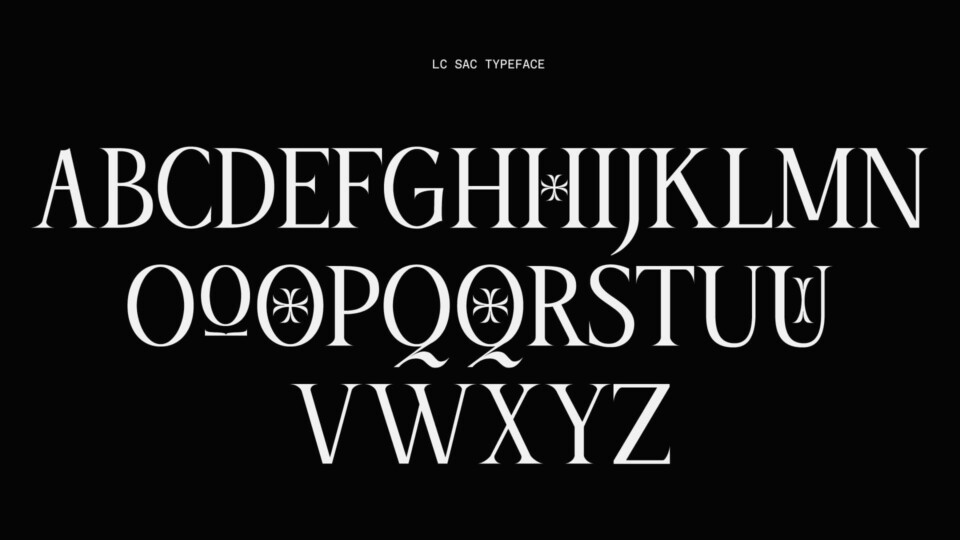
Font tiếng việt LC Sac Display – Nguyễn Quang Duy
Giới thiệu về Font tiếng việt LC Sac Display – Nguyễn Quang Duy
Trong thế giới sáng tạo, việc lựa chọn một bộ Font Miễn Phí chất lượng luôn là ưu tiên hàng đầu của các nhà thiết kế trẻ. Bộ Font tiếng việt LC Sac Display – Nguyễn Quang Duy là một tác phẩm typography đầy ấn tượng, mang phong cách hiện đại và cá tính. Đây là thành quả sáng tạo của tác giả Nguyễn Quang Duy, được tinh chỉnh kỹ lưỡng để phù hợp với bảng mã tiếng Việt, giúp người dùng không còn lo lắng về lỗi font khi soạn thảo nội dung hay làm các ấn phẩm truyền thông.
Đặc điểm nổi bật của bộ font chữ này
Sở hữu những đường nét thanh mảnh nhưng vô cùng dứt khoát, Font tiếng việt LC Sac Display – Nguyễn Quang Duy tạo nên một sự cân bằng hoàn hảo giữa tính nghệ thuật và sự chuyên nghiệp. Các chữ cái được thiết kế với độ tương phản cao, giúp tiêu đề trở nên nổi bật và thu hút ánh nhìn ngay lập tức. Đặc biệt, bộ font này rất phù hợp cho các bài thuyết trình, làm bìa sách hoặc thiết kế logo cho các dự án học đường và nghệ thuật đương đại tại Việt Nam.
Cách ứng dụng Font tiếng việt LC Sac Display – Nguyễn Quang Duy hiệu quả
Để khai thác tối đa vẻ đẹp của Font tiếng việt LC Sac Display – Nguyễn Quang Duy, bạn nên sử dụng nó cho các tiêu đề lớn (Headline) hoặc các đoạn văn ngắn mang tính nhấn mạnh. Do đặc thù là một font thuộc dòng Display, nó sẽ phát huy tác dụng tốt nhất ở kích thước chữ lớn. Kết hợp bộ font này với các tông màu tối giản như đen, trắng hoặc pastel sẽ giúp thiết kế của bạn trở nên sang trọng và tinh tế hơn bao giờ hết.